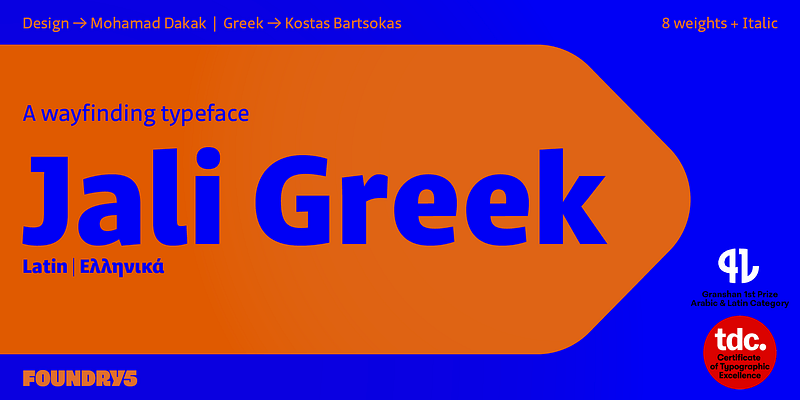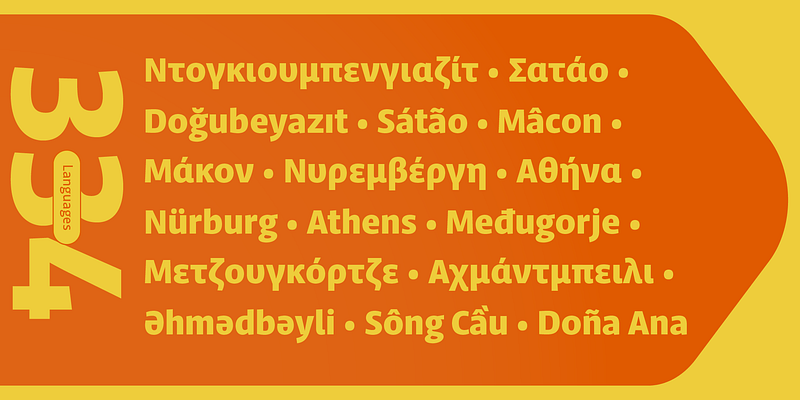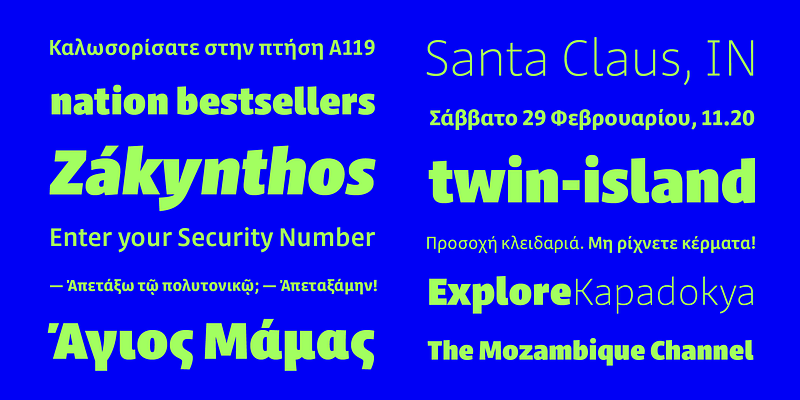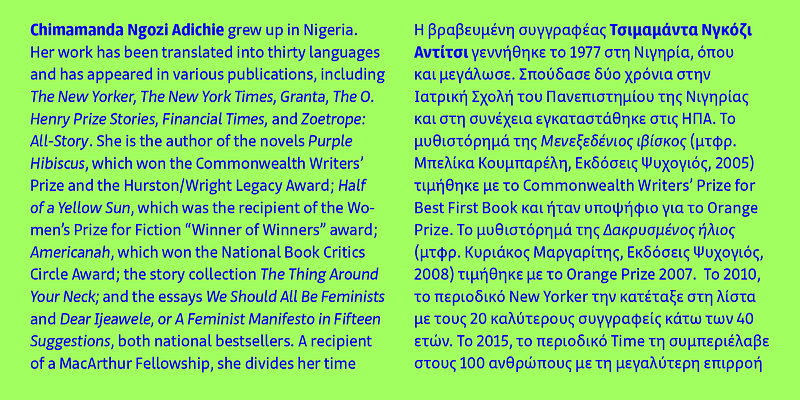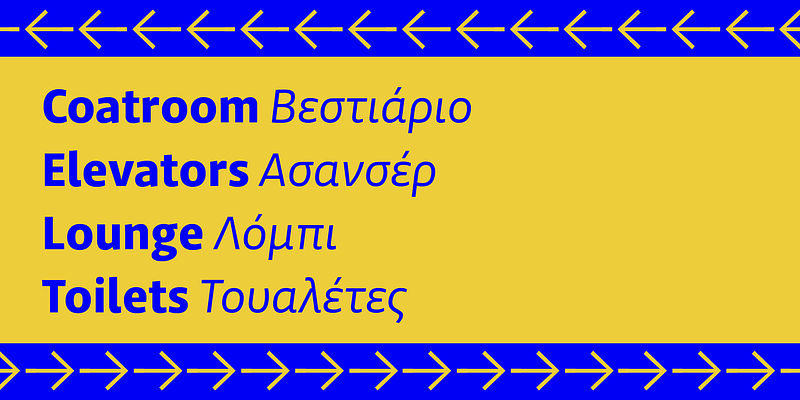
Jali es un tipo de letra sans serif humanista especialmente diseñado para la orientación. Jali combina árabe, griego y latín en una cordial armonía a la par que mantiene una voz nativa para todos los tipos de letra.
El concepto de diseño comenzó como un proyecto de graduación motivado por la falta de tipos de letra árabes que cumplieran con éxito requisitos de diseño y legibilidad exigentes. Posteriormente, el proyecto salió al mercado y se amplió para que la familia tipográfica alcanzara su máximo potencial en los tipos de letra compatibles.
El nombre “Jali” significa “claro” en árabe, y su diseño refleja el espíritu de ese nombre. La combinación de trazos de bajo contraste, blancos internos amplios, puntos y marcas distintivos hacen de Jali un tipo de letra versátil. Con su voz humanista y letras claras, Jali tiene como objetivo ofrecer una experiencia de lectura cálida y eficiente. Al igual que otras familias de tipos de letra de orientación, Jali también es ideal para entornos tipográficos exigentes.